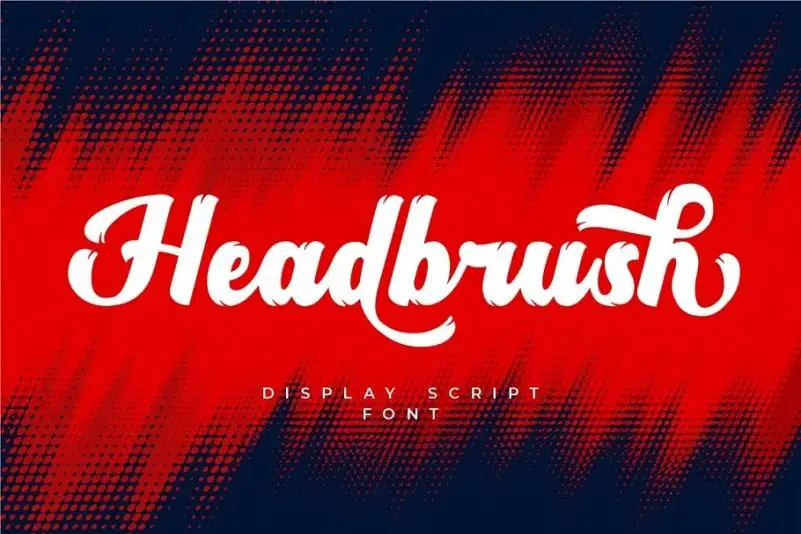
Headbrush Script Font – Download Grátis
Headbrush Script Font é uma elegante fonte de estilo script que apresenta um nível de linha variável, linhas suaves, modernidade e profundidade. Sua característica mais marcante é a adição de efeitos de caneta em cada caractere, o que lhe confere um toque único e distintivo. Esta fonte foi criada pelo estúdio 99designs por meio do designer PutraCetol Studio. Com seu estilo bold script e efeitos de caneta brilhantes, Headbrush Script Font é perfeito para qualquer projeto que busque uma mistura sofisticada de modernidade e elegância, combinando design minimalista com a tradição da escrita manual. Seja você um designer gráfico ou fotógrafo, este fonte oferece a liberdade para expressar sua criatividade em cada trabalho de arte final.